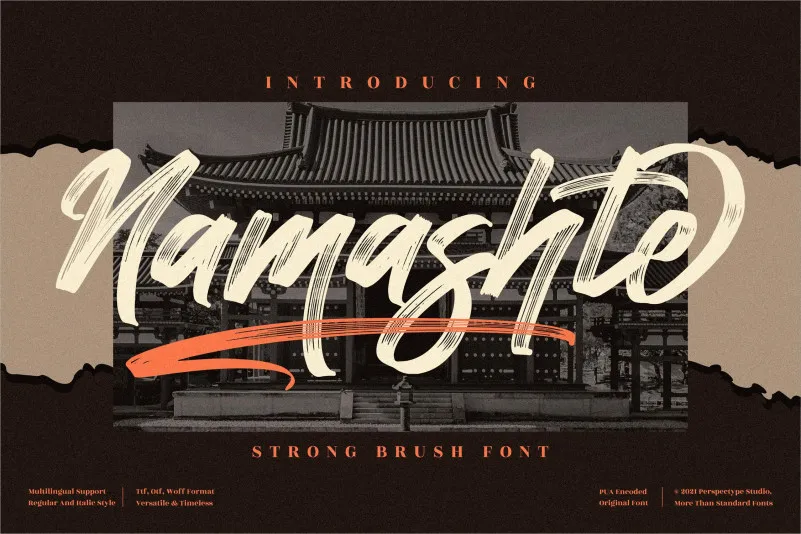
Namashte Font – Fonte Grátis
Namashte Font
A fonte Namashte é perfeita para aqueles que buscam uma aparição moderna e agressiva ao mesmo tempo delicada. Esta é uma tipografia brush script que destaca-se em designs pessoais como cartões de agradecimento, convites de casamento, anúncios de casamento e até mesmo logotipos. Suas linhas sóbrias e elegantes se assemelham perfeitamente à necessidade por um estilo único, seja para uma noiva ou apenas para personalizar sua identidade visual em um negócio. Este é o tipo de font que enriquecerá seus projetos digitais com um toque autêntico e sofisticado, tornando-o uma escolha inteligente se estiver procurando por algo novo, elegante e de alta qualidade. Namashte foi criada pelo designer perspectype, especializado em tipos brush script. Sua característica principal é a combinação perfeita entre modernidade e personalização, permitindo que você personalize cada projeto de forma única. Essa font é ideal para designers, freelancers ou profissionais do design que buscam adicionar um toque sofisticado a seus trabalhos digitais. Com Namashte, você pode criar cartões de agradecimento elegantes e criativos, logotipos impactantes e até mesmo layouts incríveis para anúncios de casamento. Ainda mais, ela é ideal para uso em aplicações de escrita digital e multimídia, tornando-a uma fonte versátil que se adapta a diferentes necessidades de design.